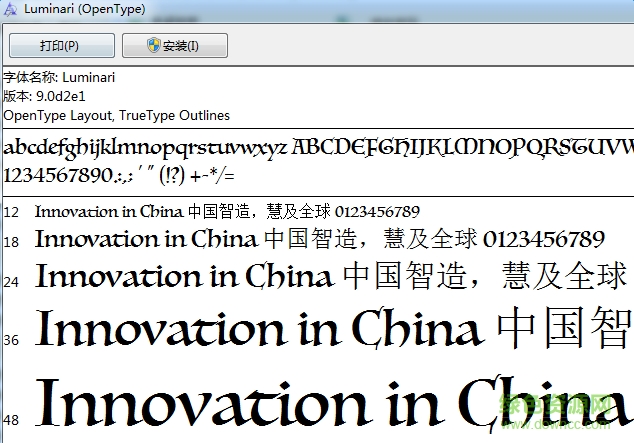
Luminari英文字體
Luminari字體是一款英文字體庫中的個(gè)性字體,該字體以其飄逸個(gè)性,讓許多設(shè)計(jì)行業(yè)的用戶深有體會(huì),有需要的朋友可以免費(fèi)下載收藏。
Luminari字體
Luminari字體是一款極具個(gè)性的字體,該字體十分飄逸,彰顯了自己的個(gè)性,有喜歡的朋友可以來綠色資源網(wǎng)下載使用!